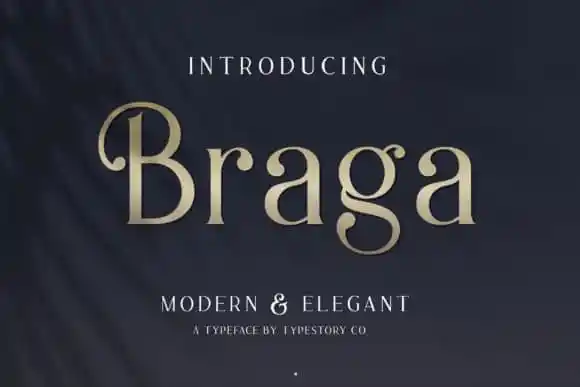
Braga Serif Font – Fonte Grátis
Braga Serif Font
A Braga Serif Font é uma seleção perfeita para quem busca tanto a elegância quanto a seriedade no design tipográfico. Essa fonte serif simples e moderna, criada pelo designer Typestory, traz consigo um toque de frescor ao mesmo tempo que mantém um ar formal e sofisticado. Ideal para projetos de design que buscam uma atitude casual mas não descolada, Braga é a escolha certa. Suas linhas são elegantes e bem definidas, oferecendo um toque de modernidade sem deixar de lado o charme pessoal da serif. A sua simplicidade lhe dá liberdade para incorporá-la em diversos projetos, desde uma criação minimalista até um design industrial, garantindo que ela se destaque e aprimore qualquer projeto. O brilho único dessa fonte faz dela uma opção ideal para quem busca criar design visual inovador e contemporâneo sem sacrificar a elegância tradicional dos estilos serif. Sempre moderna e sempre sofisticada, Braga é um excelente parceiro para seu próximo projeto de design.